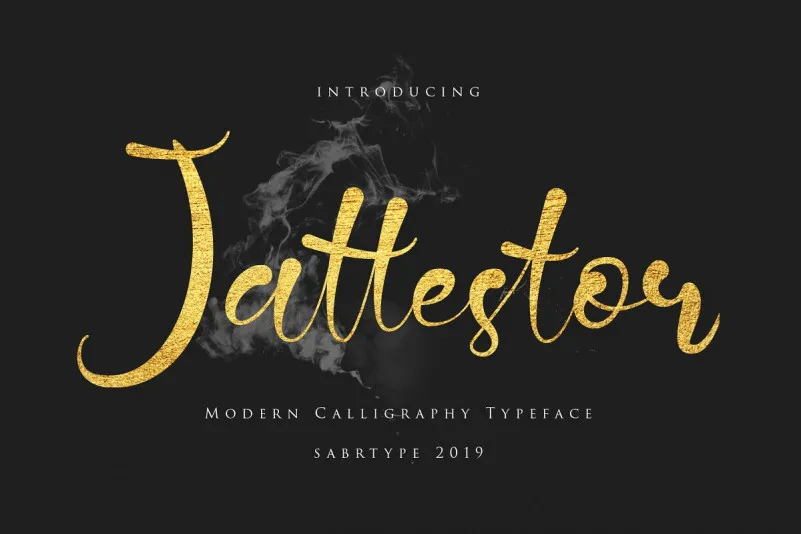
Jattestor Script Font – Fonte Grátis
Jattestor Script Font
A Jattestor Script Font é uma moderna tipografia moderna que se destaca com suas linhas simples e elegantes criadas pela sabrcreative. Esta fonte tem um gosto versátil, capaz de dar vida a designs tanto vintage quanto contemporâneos, fazendo-a perfeita para uma ampla variedade de projetos, desde logotipos e identidades corporativas até materiais de convites, notas de agradecimento, embalagens de produtos, fotografias, e muito mais. Inspirada pela sabrtype studio em seu estilo moderno e sofisticado, a Jattestor Modern Calligraphy Typeface é uma escolha ideal para aqueles buscando um estilo arredondado que se destaca sem deixar de estar atual. Sua versatilidade permite que designers profissionais criem designs impressionantes em diversos canais, incluindo posts no Instagram e redes sociais, anúncios e até mesmo marcas em fotografias ou cartões de visita para eventos especiais. A Jattestor Modern Calligraphy Typeface é um recurso gráfico indispensável para qualquer designer que busque uma fonte moderna e elegante para suas criações.